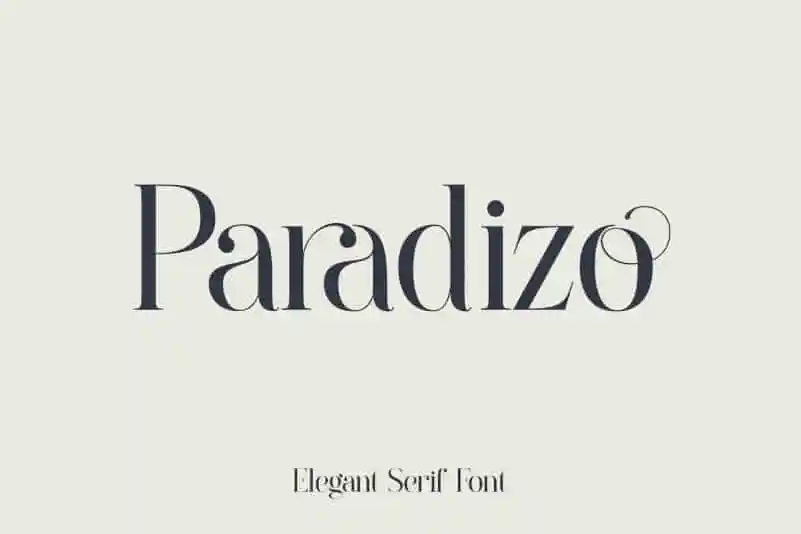
Paradizo Serif Font – Download Grátis
A Paradizo Serif é uma nova adição à nossa seleção de fonts serif que traz ao design gráfico uma experiência elegante e sofisticada. Desenhada pela Surplus Type Co., essa fonte serifa não apenas oferece versões regular e obliú, mas também um vasto leque de alternativas e ligaturas, permitindo que designers criem designs luxuosos com facilidade. Através da sua variedade extensa de alternativas e ligaturas, a Paradizo Serif torna-se uma escolha ideal para quem procura personalização. Com este tipo fonte serifa, você pode criar trabalhos impecáveis sem preocupações sobre o formato ou a língua específica do seu projeto. Através de sua versatilidade, ela se adapta perfeitamente à criação de designs em português brasileiro e outros idiomas que são comuns na comunicação digital contemporânea. Neste contexto de design gráfico cada vez mais diversificado e globalizado, a Paradizo Serif oferece um toque único e sofisticado que enriquecerá qualquer projeto. Não apenas é uma excelente opção para designers profissionais, mas também pode ser usada por indivíduos com talento para criar trabalhos de alta qualidade em suas próprias produções. Portanto, não hesite em experimentar a Paradizo Serif — ela certamente adicionará um toque singular e refinado a qualquer projeto que você estiver criando.